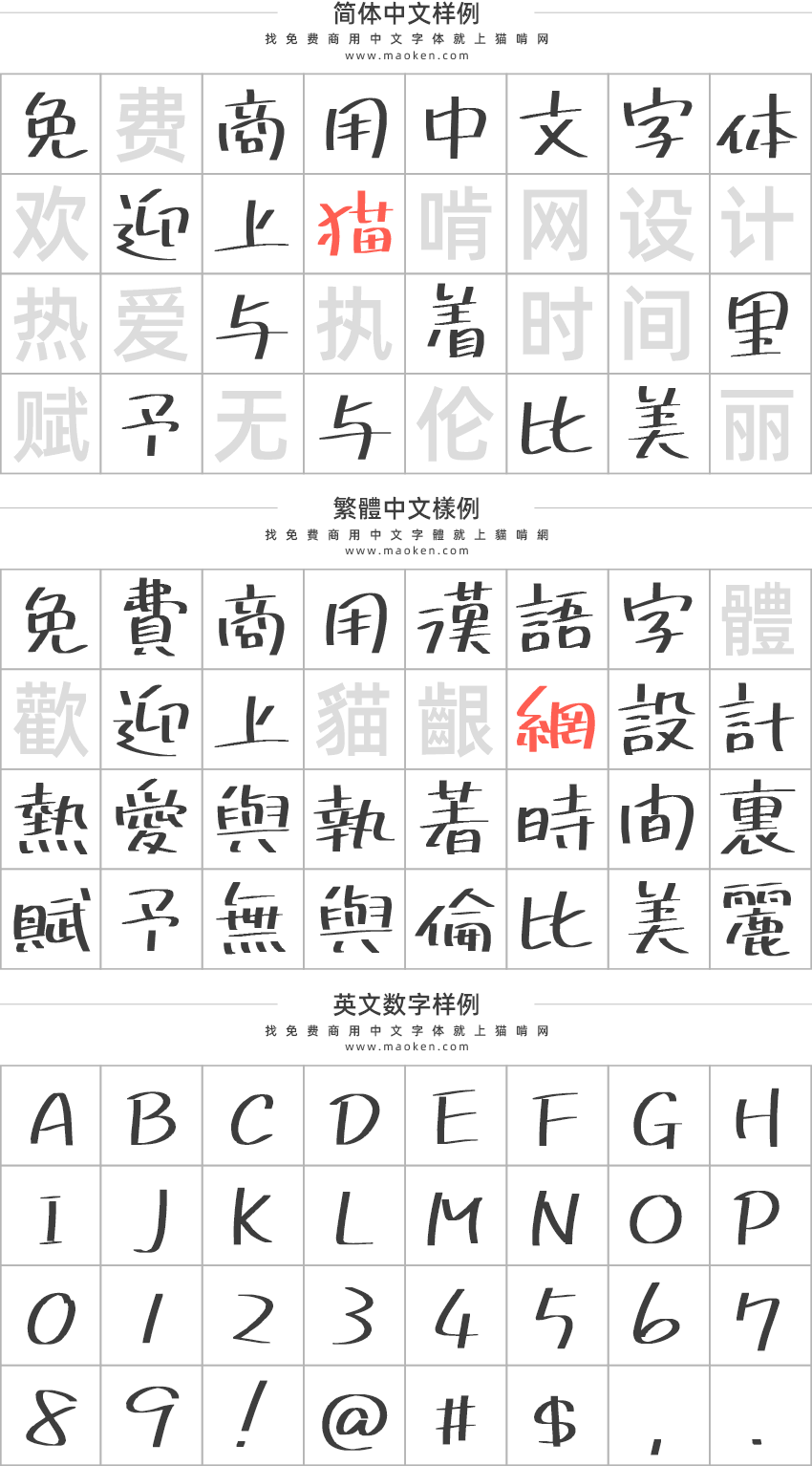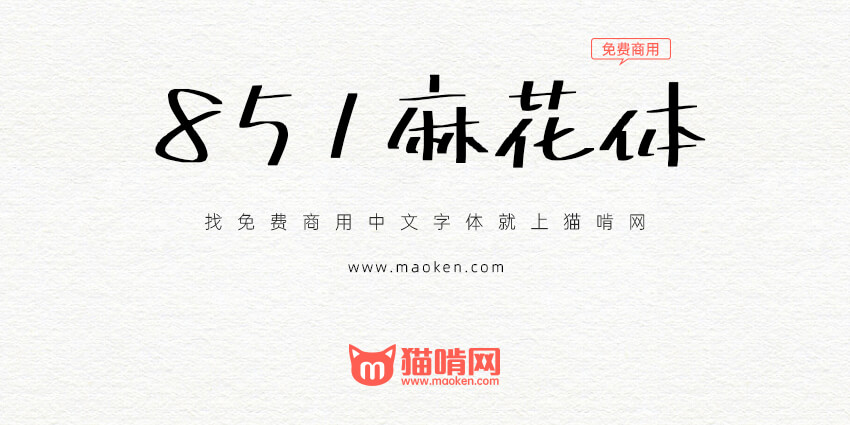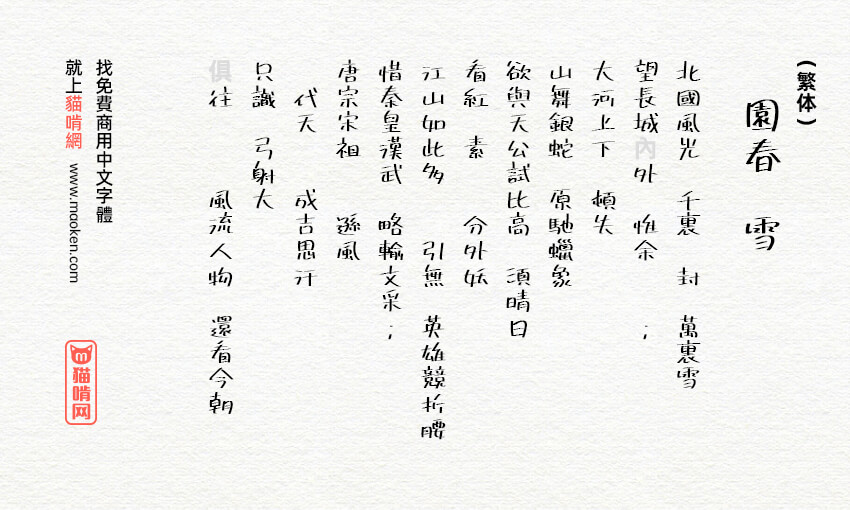
851麻花POP体:日系横粗的手写POP字体 免费商用
851麻花POP体(日文名:851マカポップ)是日本设计师 8:51:22 pm设计的一款免费商用日文字体。但是这款字体由于是日本设计师制作的,对于简体中文支持程度较差。虽然在字数统计软件中GB2312编码的有4442个字符,但是有相当一部分是空白的占位符,所以简体体验不佳。